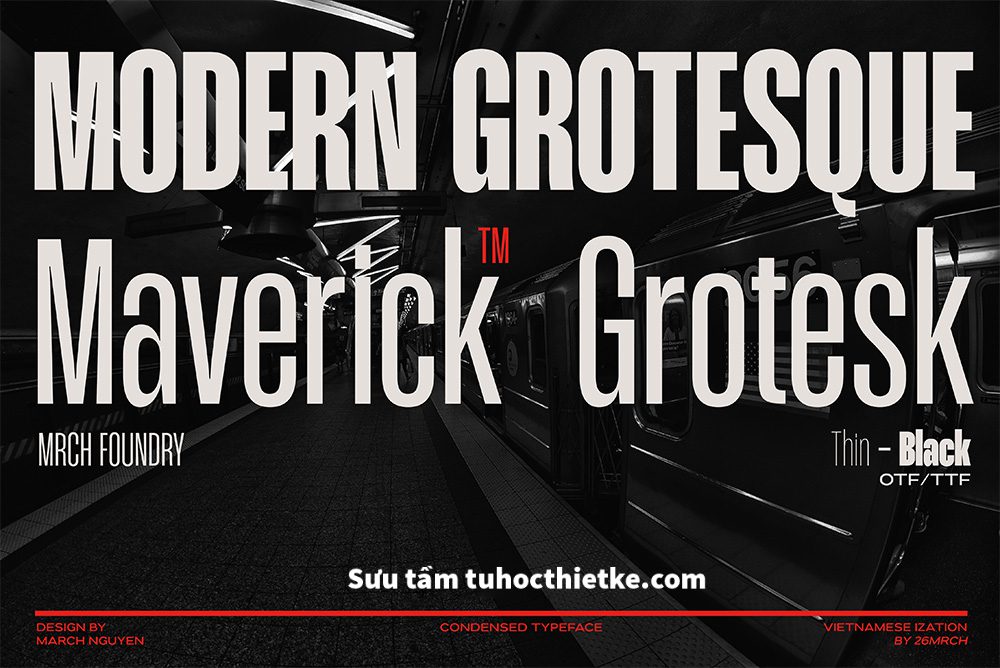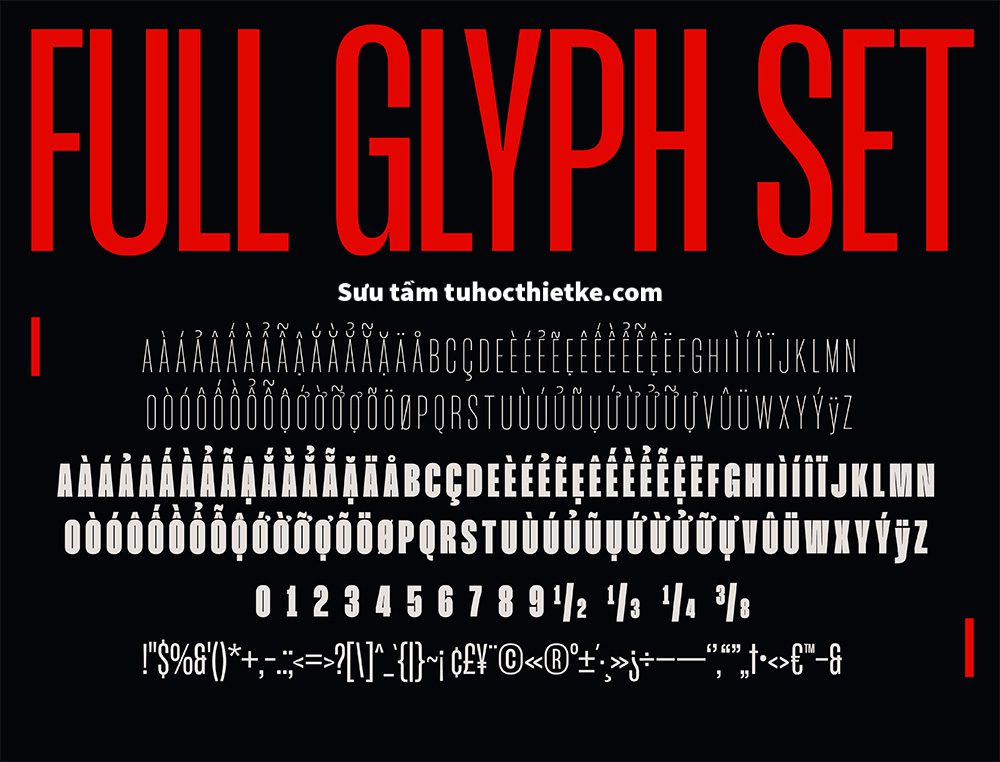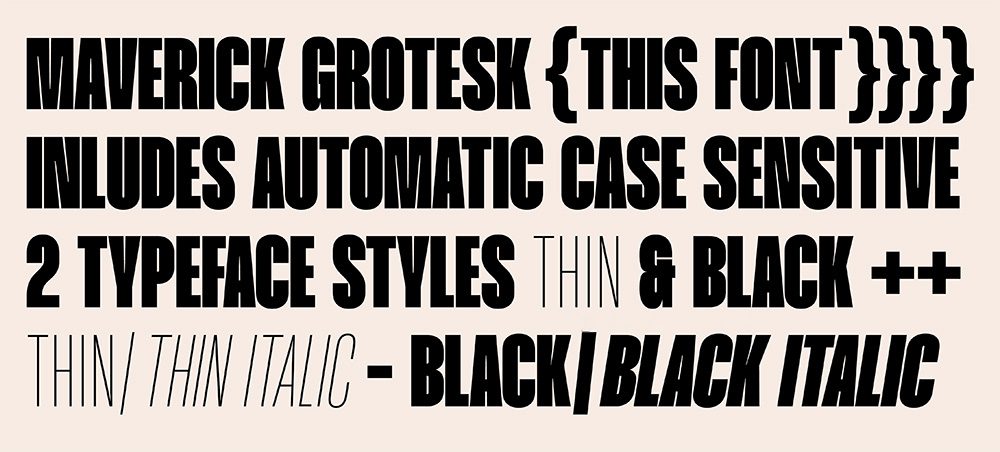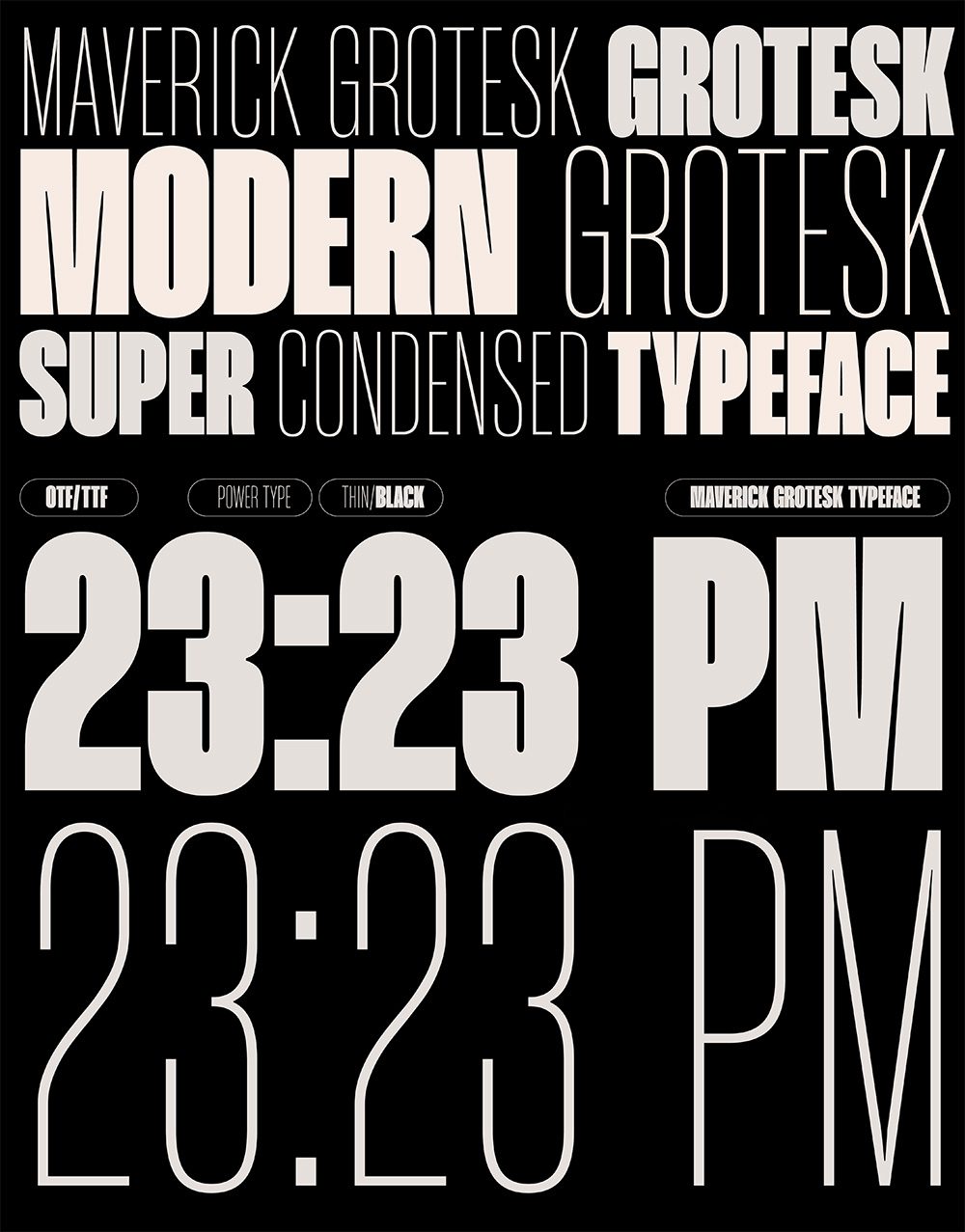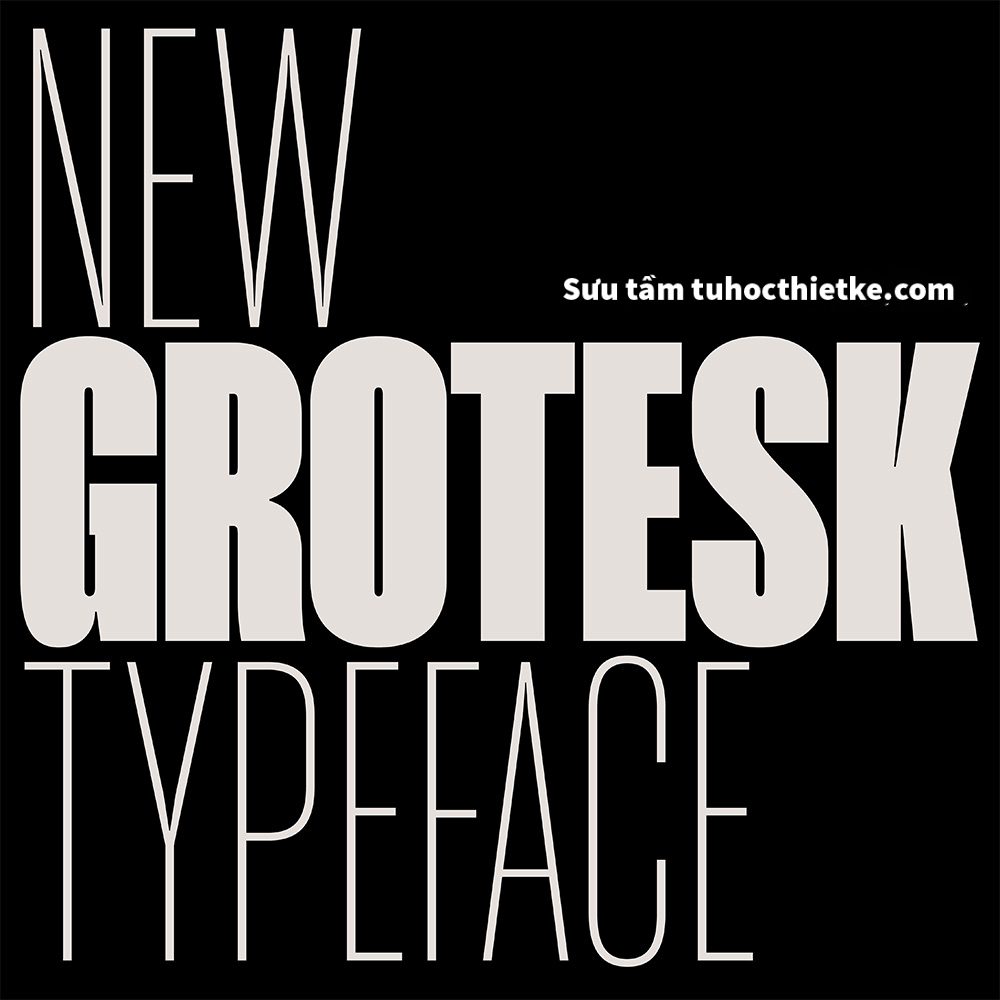
Tải Font Việt Hóa Maverick Grotesk là lựa chọn phù hợp dành cho designer đang tìm kiếm một kiểu chữ hiện đại, gọn gàng và có khả năng tạo điểm nhấn mạnh trong các thiết kế chuyên nghiệp. Với phong cách Grotesk kết hợp dáng chữ Condensed, Maverick Grotesk mang đến cảm giác chắc chắn, tối giản nhưng vẫn nổi bật. Đây là kiểu font rất thích hợp cho poster, banner, tiêu đề website, thiết kế thương hiệu, bìa sách, ấn phẩm quảng cáo và nhiều dự án sáng tạo khác.
Trong thiết kế đồ họa hiện đại, font chữ không chỉ đơn thuần là công cụ truyền tải nội dung mà còn góp phần thể hiện cá tính thương hiệu. Một font chữ đẹp có thể giúp bố cục trở nên chuyên nghiệp, dễ đọc và giàu cảm xúc hơn. Đặc biệt, với các dự án sử dụng tiếng Việt, việc lựa chọn font hỗ trợ đầy đủ dấu tiếng Việt là yếu tố rất quan trọng để đảm bảo tính thẩm mỹ và khả năng ứng dụng thực tế.
Font Maverick Grotesk Là Gì?
Maverick Grotesk là kiểu chữ mang tinh thần hiện đại, mạnh mẽ và tối giản. Phong cách Grotesk thường được biết đến với đường nét rõ ràng, ít chi tiết thừa, tạo cảm giác chuyên nghiệp và dễ ứng dụng trong nhiều lĩnh vực thiết kế. Khi kết hợp với kiểu chữ Condensed, font trở nên thon gọn hơn về chiều ngang, giúp tiết kiệm không gian mà vẫn giữ được độ nổi bật cần thiết.
Điểm đáng chú ý của Maverick Grotesk nằm ở dáng chữ chắc chắn, cấu trúc cân đối và khả năng hiển thị tốt trong các tiêu đề lớn. Font phù hợp với những thiết kế cần sự mạnh mẽ, hiện đại, nam tính hoặc mang hơi hướng editorial. Với phiên bản Việt hóa, designer có thể sử dụng font trong các nội dung tiếng Việt mà không gặp lỗi dấu, sai ký tự hoặc mất tính đồng bộ trong bố cục.
Vì Sao Nên Chọn Font Việt Hóa Cho Thiết Kế?
Hỗ Trợ Đầy Đủ Dấu Tiếng Việt
Một trong những vấn đề phổ biến khi dùng font nước ngoài là không hỗ trợ đầy đủ ký tự tiếng Việt. Khi nhập nội dung có dấu, font có thể bị lỗi, mất dấu hoặc tự động chuyển sang kiểu chữ khác, khiến thiết kế trở nên thiếu chuyên nghiệp. Vì vậy, các bộ font Việt hóa luôn được designer Việt Nam quan tâm.
Khi sử dụng font đã được Việt hóa tốt, bạn có thể yên tâm thiết kế các nội dung như tiêu đề, slogan, mô tả sản phẩm, bài đăng mạng xã hội hoặc ấn phẩm in ấn bằng tiếng Việt. Điều này giúp sản phẩm cuối cùng đồng bộ hơn và giữ được vẻ đẹp nguyên bản của font chữ.
Tối Ưu Cho Dự Án Thương Hiệu
Font chữ có ảnh hưởng rất lớn đến nhận diện thương hiệu. Với Maverick Grotesk, phong cách Condensed giúp thương hiệu trông hiện đại, gọn gàng và nổi bật hơn. Kiểu chữ này đặc biệt phù hợp với các thương hiệu thời trang, công nghệ, thể thao, sáng tạo nội dung, studio thiết kế hoặc các dự án truyền thông cần hình ảnh mạnh mẽ.
Việc Tải Font Việt Hóa chất lượng giúp designer có thêm lựa chọn khi xây dựng bộ nhận diện, thiết kế logo phụ, headline, poster hoặc các ấn phẩm quảng bá thương hiệu.
Đặc Điểm Nổi Bật Của Maverick Grotesk Condensed
Kiểu Chữ Condensed Gọn Gàng Và Ấn Tượng
Condensed là dạng chữ có chiều ngang hẹp hơn so với font thông thường. Ưu điểm của kiểu chữ này là giúp tiết kiệm diện tích trong bố cục, đặc biệt khi cần đặt tiêu đề dài trong không gian hạn chế. Dù có dáng hẹp, font vẫn giữ được sự rõ ràng và dễ đọc nếu được sử dụng đúng cách.
Maverick Grotesk Condensed rất phù hợp để làm headline lớn, tiêu đề poster, chữ trên banner hoặc các đoạn text cần tạo điểm nhấn. Khi đặt trên nền ảnh, nền màu trơn hoặc bố cục tối giản, font có thể tạo cảm giác mạnh mẽ và thu hút ánh nhìn ngay lập tức.
Phong Cách Hiện Đại, Chuyên Nghiệp
Maverick Grotesk không quá cầu kỳ nhưng vẫn có cá tính riêng. Các đường nét được xử lý gọn, dứt khoát, giúp font mang lại cảm giác chuyên nghiệp và hiện đại. Đây là lựa chọn tốt cho những designer yêu thích phong cách typography sạch, rõ ràng và có tính ứng dụng cao.
Font có thể dùng tốt trong cả thiết kế kỹ thuật số và thiết kế in ấn. Từ ảnh bìa Facebook, thumbnail YouTube, poster sự kiện, catalogue, lookbook cho đến layout website, Maverick Grotesk đều có thể phát huy hiệu quả nếu được phối hợp hợp lý với màu sắc và hình ảnh.
Dễ Kết Hợp Với Nhiều Loại Font Khác
Một ưu điểm khác của font Grotesk Condensed là dễ kết hợp với nhiều kiểu chữ khác. Bạn có thể dùng Maverick Grotesk cho tiêu đề chính, sau đó kết hợp với font sans serif đơn giản cho phần nội dung phụ. Nếu muốn thiết kế có chiều sâu hơn, có thể phối cùng font serif thanh lịch hoặc font script nhẹ nhàng để tạo sự tương phản.
Tuy nhiên, khi kết hợp font, bạn nên giới hạn khoảng 2 đến 3 kiểu chữ trong một thiết kế. Việc dùng quá nhiều font cùng lúc có thể khiến bố cục bị rối và làm giảm tính chuyên nghiệp.
Ứng Dụng Của Maverick Grotesk Trong Thiết Kế
Thiết Kế Poster Và Banner
Với dáng chữ Condensed nổi bật, Maverick Grotesk rất phù hợp cho các thiết kế poster và banner cần tiêu đề lớn. Font giúp phần chữ chiếm ít diện tích hơn nhưng vẫn giữ được sức hút thị giác. Đây là lợi thế lớn khi bạn cần truyền tải nhiều thông tin trong một bố cục nhỏ.
Bạn có thể sử dụng font cho poster âm nhạc, sự kiện, thể thao, thời trang, game hoặc các chiến dịch quảng cáo. Khi kết hợp với màu sắc tương phản, hình ảnh chất lượng cao và bố cục hợp lý, font sẽ giúp thiết kế trở nên mạnh mẽ hơn.
Việc Tải Font Việt Hóa Maverick Grotesk giúp designer dễ dàng sử dụng trong các dự án tiếng Việt mà vẫn đảm bảo tính thẩm mỹ và sự đồng bộ của thiết kế. Nếu bạn đang cần một font chữ mạnh mẽ, dễ ứng dụng và có phong cách Condensed nổi bật, Maverick Grotesk là tài nguyên rất đáng để bổ sung vào bộ sưu tập font thiết kế của mình.